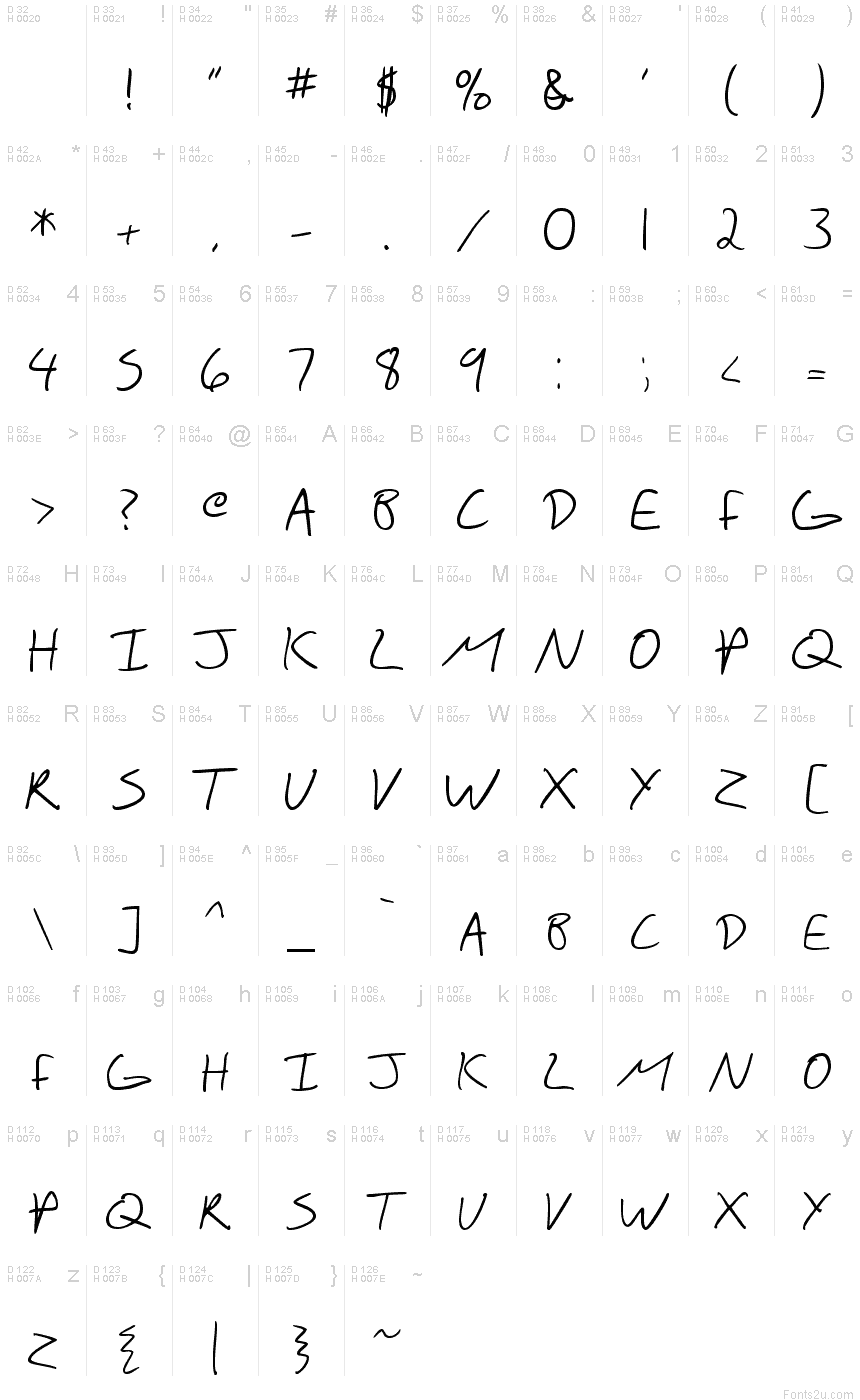
SF Scribbled Sans SC, darmowy krój pisma od ShyFoundry, to pisane ręcznie wielkie litery w stylu „scribble”. Całość wygląda, jakby została szybko naszkicowana markerem, z luźnymi krzywymi i długimi, śmiałymi pociągnięciami. Litery są lekkie i niezobowiązujące, a nierówne łączenia oraz otwarte formy sprawiają, że alfabet „żyje”, zamiast wpadać w sztywne, formalne ramy.
To naturalny wybór do nagłówków na plakatach, okładek płyt, fanzinów, grafiki skejtowej i nieformalnego brandingu, gdzie font ma wyglądać na improwizowany, a nie „wycyzelowany”. Sięgnij po niego, gdy potrzebujesz krótkich nagłówków, tekstów na okładki lub inicjałów w stylu monogramów, które niosą ze sobą niespokojną, odręczną energię, nie przypominając przy tym liter z kreskówek.
SF Scribbled Sans SC